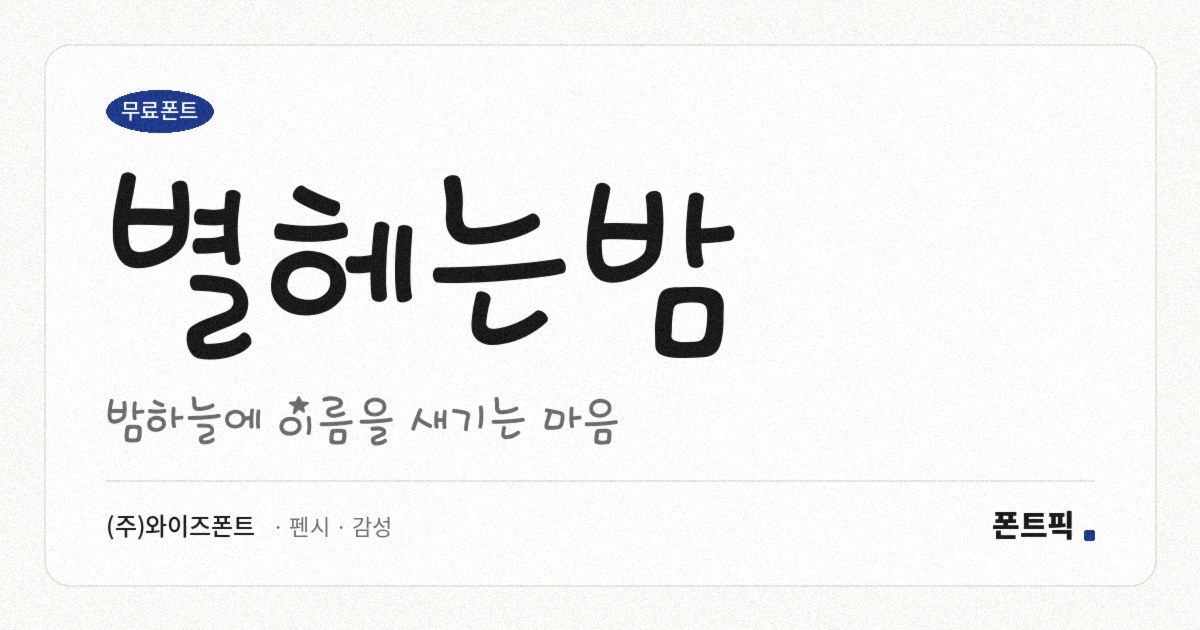
별헤는밤 서체 견본
별헤는밤
TDTDStarlightNight
별헤는밤 소개
모음 옆에 작은 별이 하나씩 떠 있는 손글씨 서체입니다. 나의 곁줄기 자리처럼 획이 비는 곳에 별이 들어가 있어, 글자를 치면 자연스럽게 별이 흩뿌려집니다.
형태는 가볍습니다. 파일에서 재어 보면 획이 가늘고 자면을 채우는 비율이 낮은 편이며, 가로획이 세로획보다 오히려 굵어서 펜을 옆으로 뉘어 쓴 듯한 인상을 냅니다. 받침이 붙을 때 글자가 0.28em 아래로 내려가는 탈네모틀이라 글줄이 공책에 쓴 것처럼 오르내립니다.
획이 가늘고 사이가 넉넉해 인상이 차분한 편이라 밤이나 꿈, 계절처럼 감성적인 낱말과 잘 붙습니다. 다만 별 장식은 반복되면 금세 지루해지니 제목 한 줄에만 쓰고 본문은 다른 서체에 맡기는 편이 낫습니다. 현대 한글 11,172자를 모두 담았고 굵기는 하나입니다.